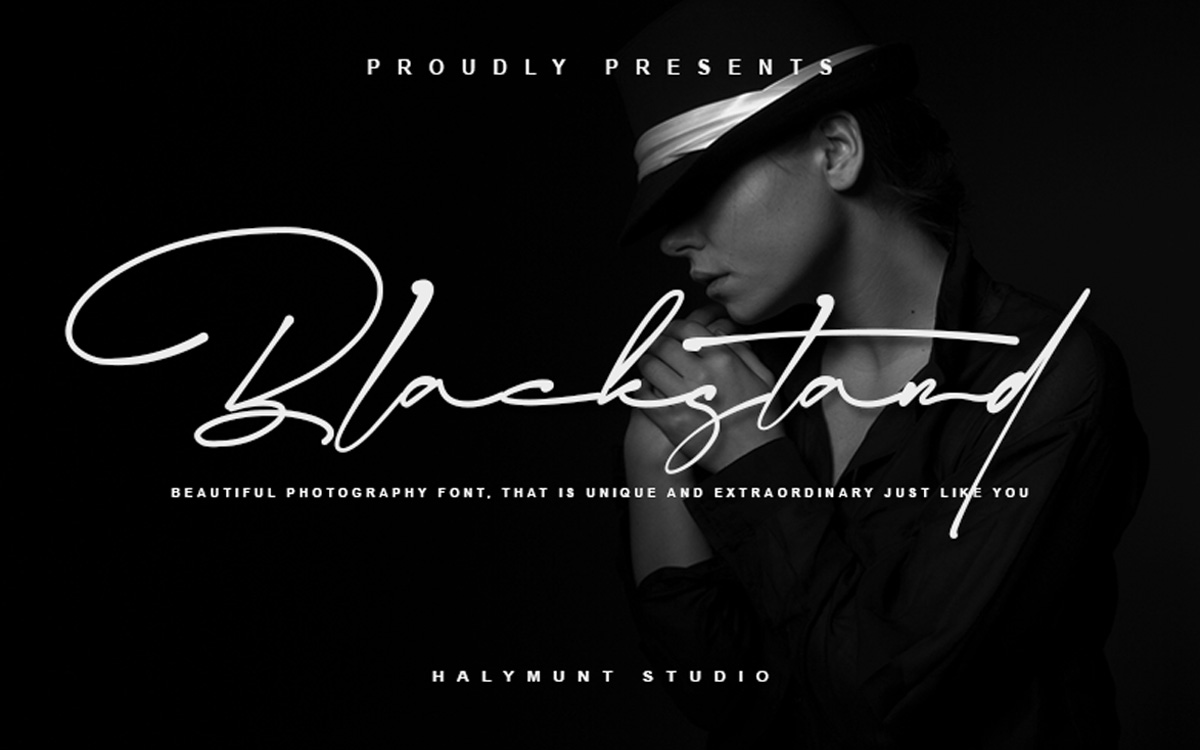
Font chữ viết tay, chữ ký mềm mại cho thiệp cưới, đám cưới TH Blackstand
Trong không gian thiết kế cưới hỏi hiện đại, sự kết hợp giữa nghệ thuật thư pháp và phong cách sang trọng luôn mang lại sức hút khó cưỡng cho từng tấm thiệp mừng. Font chữ viết tay, chữ ký mềm mại cho thiệp cưới, đám cưới TH Blackstand là sự lựa chọn hoàn hảo giúp thổi hồn vào từng chi tiết, tạo nên vẻ đẹp uyển chuyển, lãng mạn và vô cùng ấn tượng. Với bộ ký tự Việt hóa trọn bộ cùng nét bút tự nhiên, TH Blackstand giúp tôn vinh tên tuổi cô dâu chú rể và nâng tầm toàn bộ ấn phẩm trong ngày trọng đại.
Font Chữ Viết Tay, Chữ Ký Mềm Mại Cho Thiệp Cưới, Đám Cưới TH Blackstand – Điểm Nhấn Nghệ Thuật Cho Ngày Trọng Đại
Thiệp cưới không đơn thuần là một lời mời, mà còn là ấn tượng đầu tiên thể hiện gu thẩm mỹ, phong cách sống cũng như câu chuyện tình yêu của mỗi cặp đôi. Một tấm thiệp cưới hoàn hảo đòi hỏi sự chăm chút kỹ lưỡng từ chất liệu giấy, màu sắc cho đến font chữ hiển thị. Trong đó, phần tên của cô dâu và chú rể luôn là trung tâm của thị giác, cần một phong cách chữ vừa nổi bật vừa giàu cảm xúc.
Bộ font TH Blackstand ra đời nhằm đáp ứng trọn vẹn nhu cầu sáng tạo khắt khe đó. Được thiết kế dựa trên nét bút ký tay phóng khoáng nhưng không kém phần chỉn chu, bộ font này mang đến cảm giác chân thật, ấm áp và đong đầy tình cảm. Sự xuất hiện của TH Blackstand giúp các nhà thiết kế thiệp cưới, các agency sự kiện và chính các cặp đôi tự tay tạo nên những mẫu thiết kế độc bản, ghi lại dấu ấn khó quên trong đời.
Các Tính Năng Nổi Bật Của Font Chữ Ký TH Blackstand
Nét Chữ Bay Bổng, Mềm Mại Tự Nhiên Như Chữ Ký Tay Thật
TH Blackstand sở hữu nét bút uyển chuyển, mô phỏng hoàn hảo thao tác viết tay thực tế của một nghệ nhân calligraphy chuyên nghiệp. Các đường nối giữa các chữ cái được xử lý mượt mà, tạo nên dòng chảy thị giác liền mạch, tinh tế và tràn đầy cảm xúc. Điểm đặc biệt của nét chữ ký mềm mại này chính là độ đậm nhạt linh hoạt theo lực nhấn giả lập, tạo chiều sâu nghệ thuật độc đáo. Nhờ đó, tên của chú rể và cô dâu trên thiệp cưới sẽ xuất hiện một cách nổi bật, quyến rũ và đầy tính cá nhân hóa.
Bộ Ký Tự Việt Hóa Trọn Bộ, Chuẩn Tác Vụ Thiết Kế Chuyên Nghiệp
Một trong những thách thức lớn nhất khi dùng font chữ nước ngoài là lỗi hiển thị tiếng Việt hoặc các dấu thanh bị thô cứng, mất cân đối. Font đám cưới TH Blackstand đã được Việt hóa trọn bộ tỉ mỉ, giữ nguyên vẹn tinh thần nghệ thuật của nét chữ gốc mà vẫn đảm bảo tính chuẩn xác của ngữ pháp tiếng Việt. Các dấu hỏi, ngã, sắc, huyền, nặng hay các ký tự có dấu như ê, ô, ơ, ư đều được đặt ở vị trí tối ưu, không làm phá vỡ cấu trúc tổng thể của từ ngữ, mang đến vẻ đẹp hài hòa nhất.
Tích Hợp Hệ Thống Ký Tự Thay Thế (Stylistic Alternates) Và Swashes Đa Dạng
Để hỗ trợ tạo nên những ấn phẩm mang tính cá nhân hóa cao, TH Blackstand cung cấp hệ thống ký tự thay thế cùng các đường uốn lượn (swashes) trang trí cực kỳ đa dạng. Bạn có thể dễ dàng tùy biến chữ cái đầu tiên hoặc chữ cái kết thúc bằng những đường móc lãng mạn, hình nét bay bổng hoặc hoa văn nghệ thuật. Sự phong phú này giúp các nhà thiết kế thỏa sức biến tấu, tạo ra hàng trăm biến thể khác nhau cho tên cô dâu chú rể mà không lo bị trùng lặp hay đơn điệu.
Tương Thích Hoàn Hảo Với Nhiều Ứng Dụng Thiết Kế Và Công Nghệ In Ấn
Font chữ thiệp cưới TH Blackstand được tối ưu hóa chuẩn vector cao cấp, đảm bảo không bị vỡ nét hay mờ nhòe dù thu nhỏ làm chi tiết phụ hay phóng to trên các bảng đón khách (welcome board) kích thước lớn. Font chữ hoạt động ổn định trên các phần mềm đồ họa chuyên nghiệp như Adobe Photoshop, Adobe Illustrator, CorelDraw, Canva cho đến các ứng dụng văn phòng như Microsoft Word, PowerPoint. Bên cạnh đó, cấu trúc đường nét sạch sẽ giúp font rất thuận tiện cho các công nghệ in ấn cao cấp như ép kim (foil stamping), dập nổi (embossing), in UV hoặc cắt laser trên mica, gỗ, giấy mỹ thuật.
Ứng Dụng Đa Năng Từ Thiệp Cưới Đến Nhận Diện Thương Hiệu Sang Trọng
Dù được thiết kế tối ưu cho ấn phẩm cưới hỏi, TH Blackstand không bị giới hạn trong khuôn khổ ngày cưới. Font chữ ký mềm mại này còn là lựa chọn hàng đầu cho các dự án nhận diện thương hiệu cao cấp như logo studio ảnh cưới, nhãn hàng mỹ phẩm, thời trang, thiệp mời sự kiện thượng lưu, thiết kế bìa sách, quote nghệ thuật hay watermark bảo vệ bản quyền hình ảnh. Sự linh hoạt này biến TH Blackstand thành một công cụ sáng tạo không thể thiếu đối với các designer chuyên nghiệp.
Bí Quyết Phối Font TH Blackstand Để Có Mẫu Thiệp Cưới Đẹp Xuất Sắc
Để tạo nên một tấm thiệp cưới cân đối và hợp thị giác, việc phối hợp giữa font chữ nghệ thuật chính và font chữ thông tin phụ đóng vai trò vô cùng quan trọng. Dưới đây là một số gợi ý giúp bạn ứng dụng TH Blackstand hiệu quả nhất:
• Kết hợp với Font Serif cổ điển: Sử dụng TH Blackstand cho tên cô dâu, chú rể hoặc từ “Thiệp Mời”, kết hợp với một font Serif chân phương (như Times New Roman, Bodoni, Garamond) cho phần ngày tháng và địa điểm. Sự đối lập giữa nét uốn lượn lãng mạn và nét chân phương đứng đắn tạo nên vẻ đẹp sang trọng, đẳng cấp.